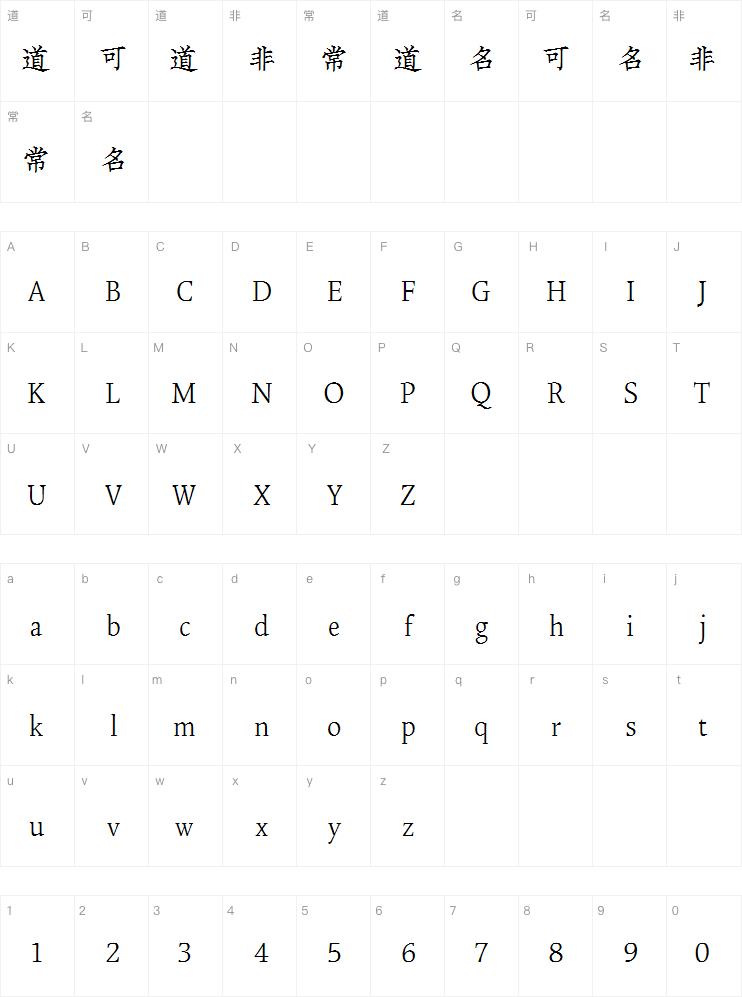
山海汲古江南宋刻,是一款全新的国风复古刻本字体,包含简繁汉字9169个,符号200+个。字形秉承中国宋代古籍善本之字形特性,字形方正,端庄严谨,古朴大方,起落顿笔有棱角,同时饱有笔墨之意。在秉承笔形间创新,结合当代设计视觉环境,融入现代审美,适用场景更多元,笔画造型清晰锐利,删繁取简,速度感强,重现宋刻本古韵之美。